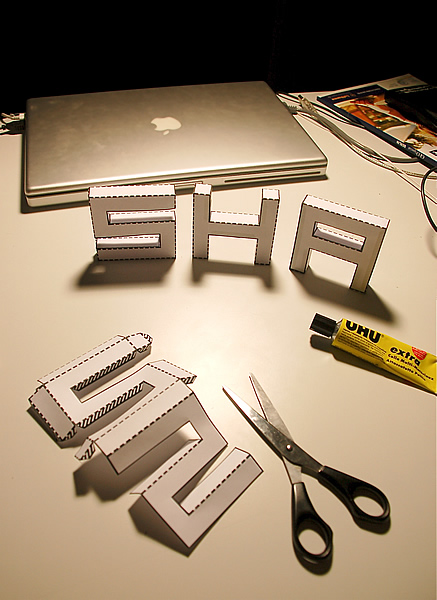
En faisant des recherches de typographie pour le boulot, je suis tombé sur cette typo : Punched Out
Cette typographie est une typographie imprimable qui représente des lettre en 3D à monter soit-même. Imprimer les lettre dont vous avez besoin sur une feuille A4 par exemple et faite vos propres mot en 3D. Perso, je trouve ca vraiment classe. Chez soi ou au boulot, vous allez surement faire sensation avec cette Punched Out typographie.